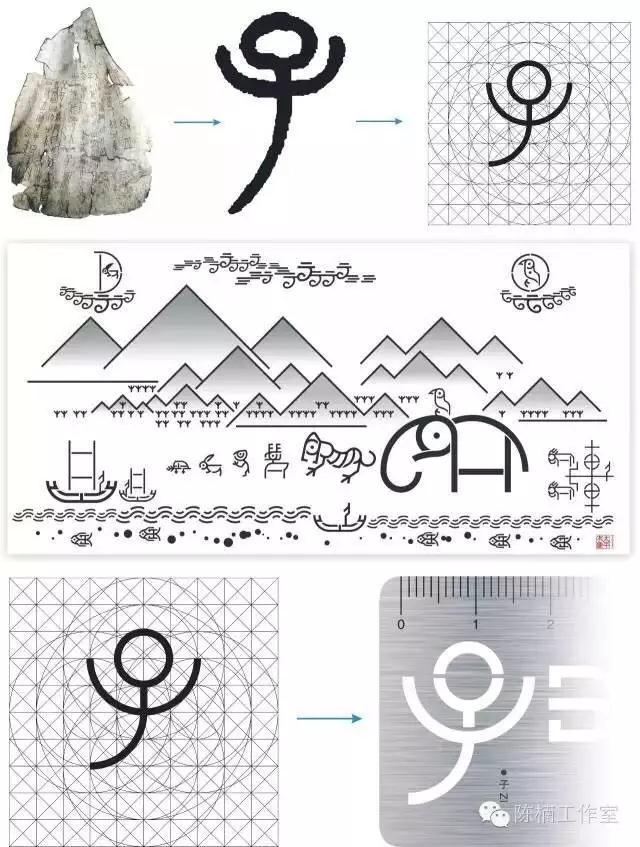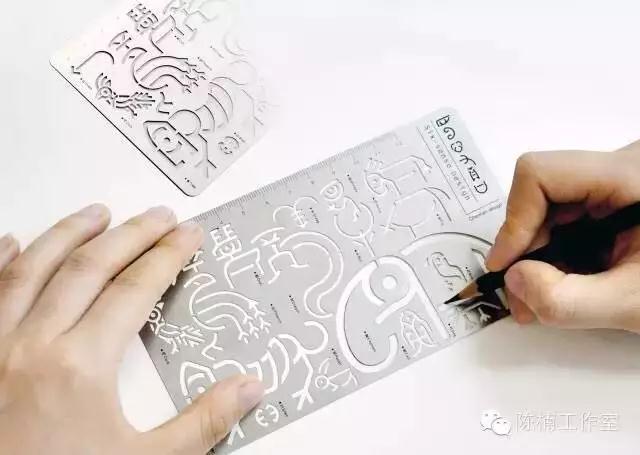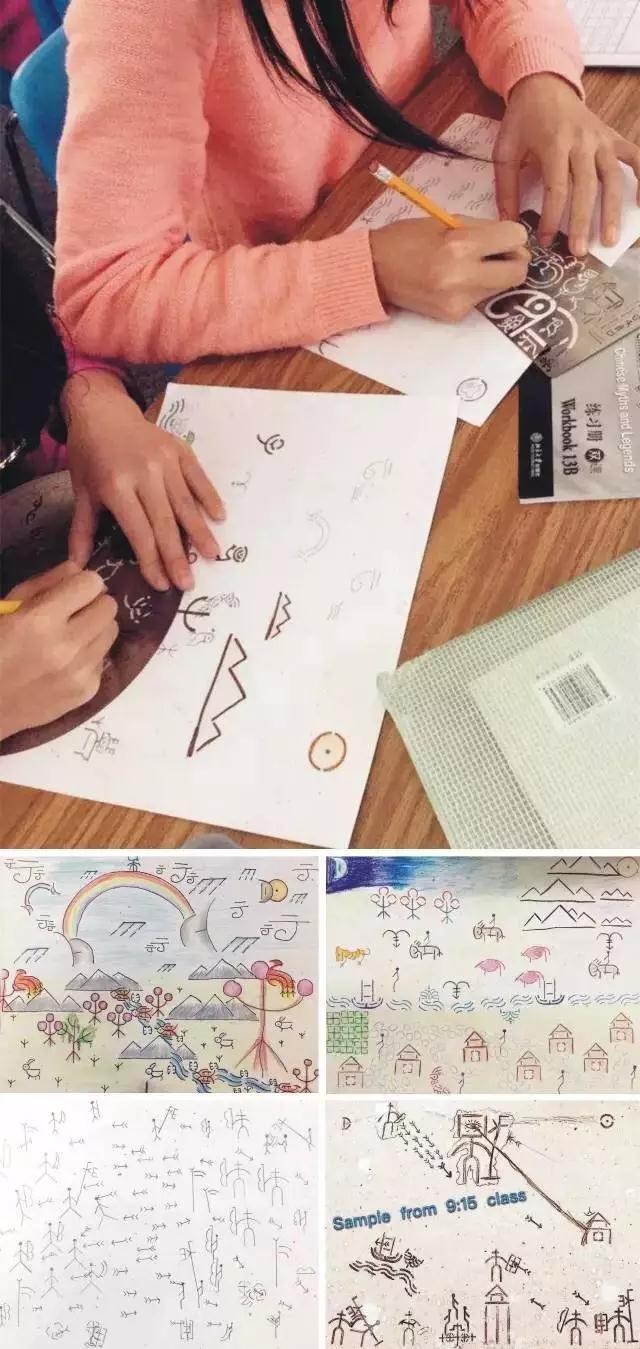
汉字文化的传承与创新,汉字创意产品化高峰论坛
由深圳出版发行集团主办,深圳市字在文化传播有限公司、深圳书城中心城联合承办的“汉字在行动—— 汉字创意产品化高峰论坛”活动圆满结束,一群热爱汉字文化,推动汉字发展的学者相聚于此,从设计研究、教学、推广、民间保护、商业发展等各个方面为汉字发声。
深圳市字在文化传播有限公司CEO刘美松先生开场致辞
论坛主持-汉仪字库首席运营官马忆原女士
汉字在行动,保护传统汉字文化,让汉字进入到我们生活的每一个细节,是我们各个领域研究推广的责任。我们从不同的维度挖掘并用自己的方式去保护、传承汉字文化,秉承时代精神,拥抱时代变化,赋予汉字当代社会价值,活化汉字传承发展。
《以心格物——我的汉字设计观》
清华大学美术学院视觉传达设计系副主任、平面设计研究所所长、中国古文字艺术研究中心副主任,汉仪字库签约字体设计师陈楠教授,从设计的角度为大家分享了关于传统汉字文化的部分研究。
陈楠从1991年考入中央工艺美院,1995年留校任教至今,已经有26年时间了,对于文字艺术与设计的研究及创作,始终是他的学术研究与创作重点。第一届艺术与科学大会上发表了“数字化甲骨文”系列作品,在设计之初比较迷恋优美的甲骨文本身以及由甲骨文构成,此后考虑比较多的是如何找到这种古老文字在当下的社会价值,如何为伟大的中华传统文化的传承与发展尽自己一份力量。
陈楠以自己独到的设计眼光重新审视传统文化中的哲学观念、思维方法,形成了自己独特的“格律设计论”,即从细究和穷究事物的最基本构成元素入手,探讨建立何种格局以及何种运行规律的设计方法论。
“数字化甲骨文字绘”是陈楠在格律设计思维下的创新设计,也是古老汉字与当下社会碰撞的结果。数字化甲骨文字绘是在一个由正“方”与正“圆”构筑的网格状母图,通过母图网格节点间的线段截取,应对复杂的汉字笔画,从而获得几何化甲骨文。
目前,汉仪字库与陈楠教授正在合作开发市面上唯一一款甲骨金古汉字的设计字体,这款字库能让更多的人了解和使用甲骨文,体验这种古老文字之美。
甲骨文绘图系列
《汉字的精神》——谈读“书”,谈“字”在
中国传统民间文化学者,汉声事业创始人黄永松先生一直在致力于抢救、保护和发扬中国民间传统文化,在这次论坛中,黄永松先生为大家带来了关于“汉字的精神”的分享,他认为汉字为书创造了生命,为大家提供了更佳品质的阅读。
在生活中,我们无时无刻不在消费汉字,汉字不仅仅是在形式上传达了信息,更重要的是汉字的精神依附形式为我们的生活拉开历史长卷,从过去到现在,再到将来,创新传承,生生不息。
由左到右依次为
汉仪字库COO马忆原
国家汉办/孔子学院综合文化处处长许亮
国际汉语学院副院长桂帆
国际设计师联盟AGI成员吴勇
论谈邀请了不同领域的几位嘉宾分别从文化、设计的维度阐述了各自对于保护发展传统汉字文化的看法。在当下社会,各个领域对于传统文化的保护已经不仅仅是拘泥在博物馆这样的场景中,而是赋予他们更多的生命,让传统文化走进生活。
由左到右依次为
汉仪字库COO马忆原
北京语言大学中国文化研究院院长张华
深圳职业技术学院讲师姜莹
深圳平面设计师协会秘书长/天诺设计创作总监张昊
传统文化不仅与学者有关,更是和我们每一个人都息息相关。不管是学术性的研究,还是产品化的发展;不管是文化教育的延续,还是设计创新的实践,从各行各业入手去挖掘汉字传承的载体,包括汉字研究、汉字教育、汉字字体设计、汉字文化衍生品等等,是我们每个人的义务和责任。
“ 各美其美,美人之美,美美与共,天下大同。”
无独有偶,汉字的创新与传承也正是国内最早的专业字库公司——汉仪字库,也将第三届字体之星设计大赛的主题定为创新与传承,在创新的设计理念之上, 鼓励所有热爱字体的设计师从创新的角度出发,提出有创造力,有梦想的字体设计方案。
让汉字在各个领域绽放光彩,在不同的载体中发扬光大,汉仪字库也将继续秉承着“创新与传承”的主旨,捕捉时代精神,让汉字拥抱变化,推动汉字在字体行业的发展,实现大同之美。
在2017年第十三届中国(深圳)国际文化产业博览交易会中心书城分会场,与这次论坛并行的活动还包括“汉字在行动——汉字文化创意展”,大家可以到现场参观体验和汉字相关的设计成果、文创产品成果、教育研究成果等。
展览部分作品
设计师吴勇作品
字体设计作品
文博会主会场“字在”品牌展览
汉字在行动——汉字文化创意展